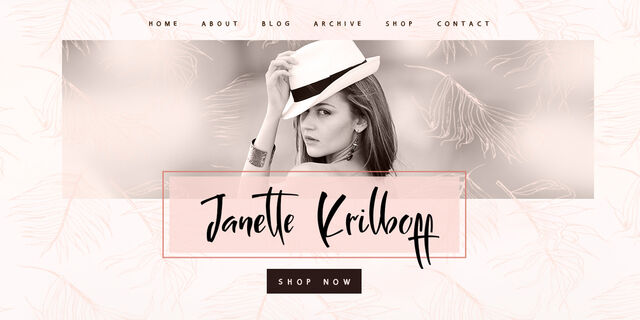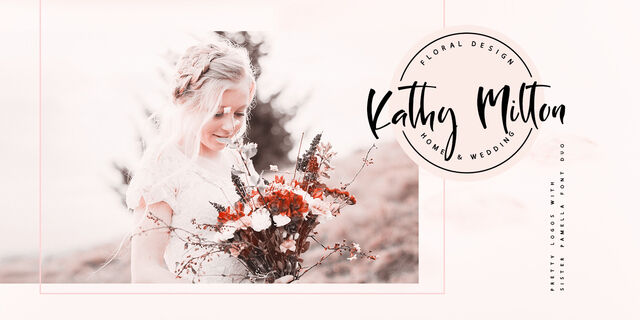
Это рукописный шрифт из шрифтовой пары Sister Pamella Font Duo Cyrillic которая в сочетании идеально подходит для использования во всех ваших дизайнерских проектах, будь то логотипы, подписи, этикетки, дизайн упаковки, заголовки блогов. Кроме того, он будет отлично смотреться на кружках, вывесках, открытках, типографических плакатах, свадебных канцелярских принадлежностях и многом другом. Sister Pamella Script включает в себя полный набор из прописных букв, 2 набора строчных букв, цифры, большой диапазон знаков препинания и 38 лигатур, что создает реалистичный стиль букв, написанных от руки. Многоязычная поддержка 31 языка на основе латиницы и кириллицы.
Шрифт разработала Ирина Двилюк в 2021 году.
быстрый, артистичный, органический, динамичный, свежий, неряшливый, веселый, легкомысленный, эмоциональный, жидкий, лихой, подвижный, непоседливый, мультяшный, яркий, вкусный, смешной, добрый, милый, мягкий, ремесленный, рукотворный, ручной, дружелюбный, доверительный, зеленый, натуральный, природный, игривый, забавный, прикольный, живой, оригинальный, приветливый, характерный, праздничный, сочный, спелый, крафтовый, радостный, озорной, весенний, летний, счастливый, прыгающий, танцующий, проворный, свободный, размашистый, модный, смелый, интересный, энергичный, темпераментный, самобытный, художественный, мечтательный, выразительный, заметный, броский, творческий, экспрессивный, активный, романтичный, приятный, красивый